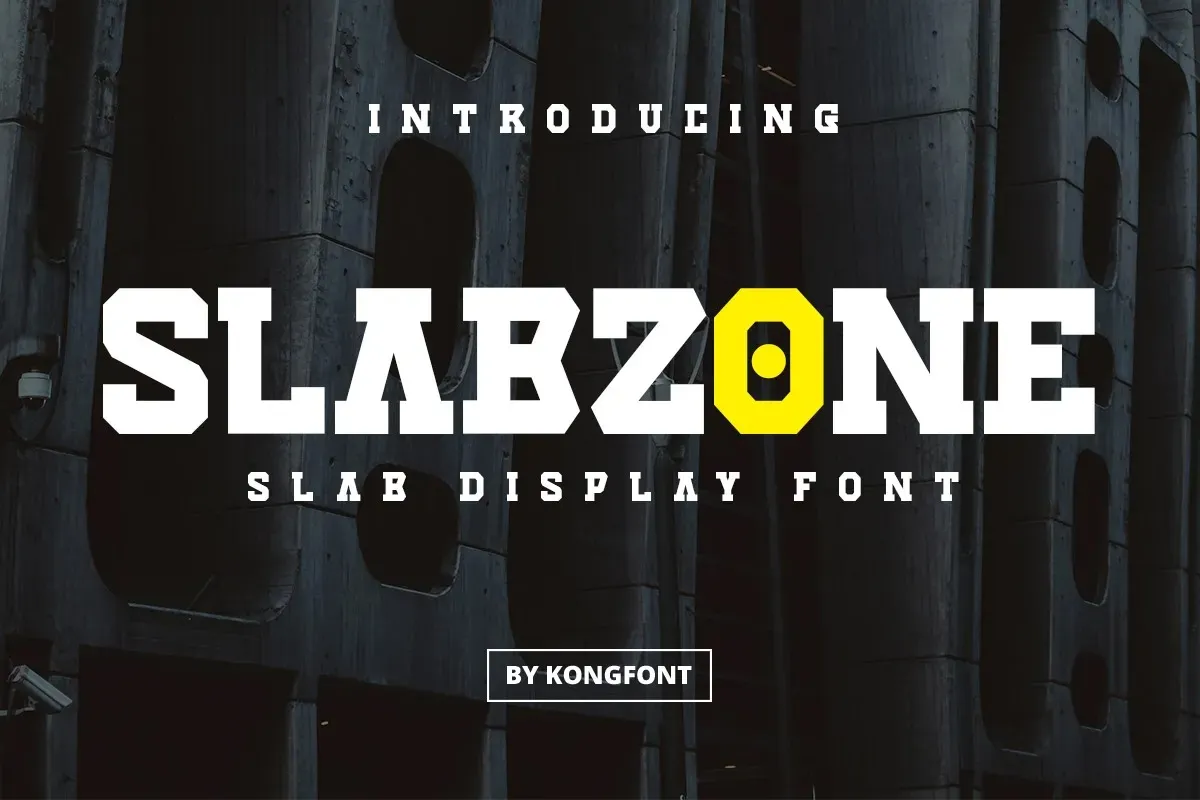
A ‘Slabzone Font’ é uma elegante serifada com forma retangular que combina várias estilos para criar este tipo moderno e arredondado. Ela surge de um designer chamado Kong Font, oferecendo-lhe um visual atraente e versátil. Ideal tanto para criar identidades visuais como em elementos digitais, essa fonte é perfeita para design gráfico, arte e publicidade. Seja você criando um logotipo ou escrevendo uma frase inspiradora para sua próxima campanha de mídia social, a ‘Slabzone Font’ está disponível para tornar seu trabalho ainda mais incrível. Ideal tanto para uso em postagem da web quanto em criações de arte digital, esta fonte é versátil o suficiente para atender às necessidades de design gráfico moderno e elegante.